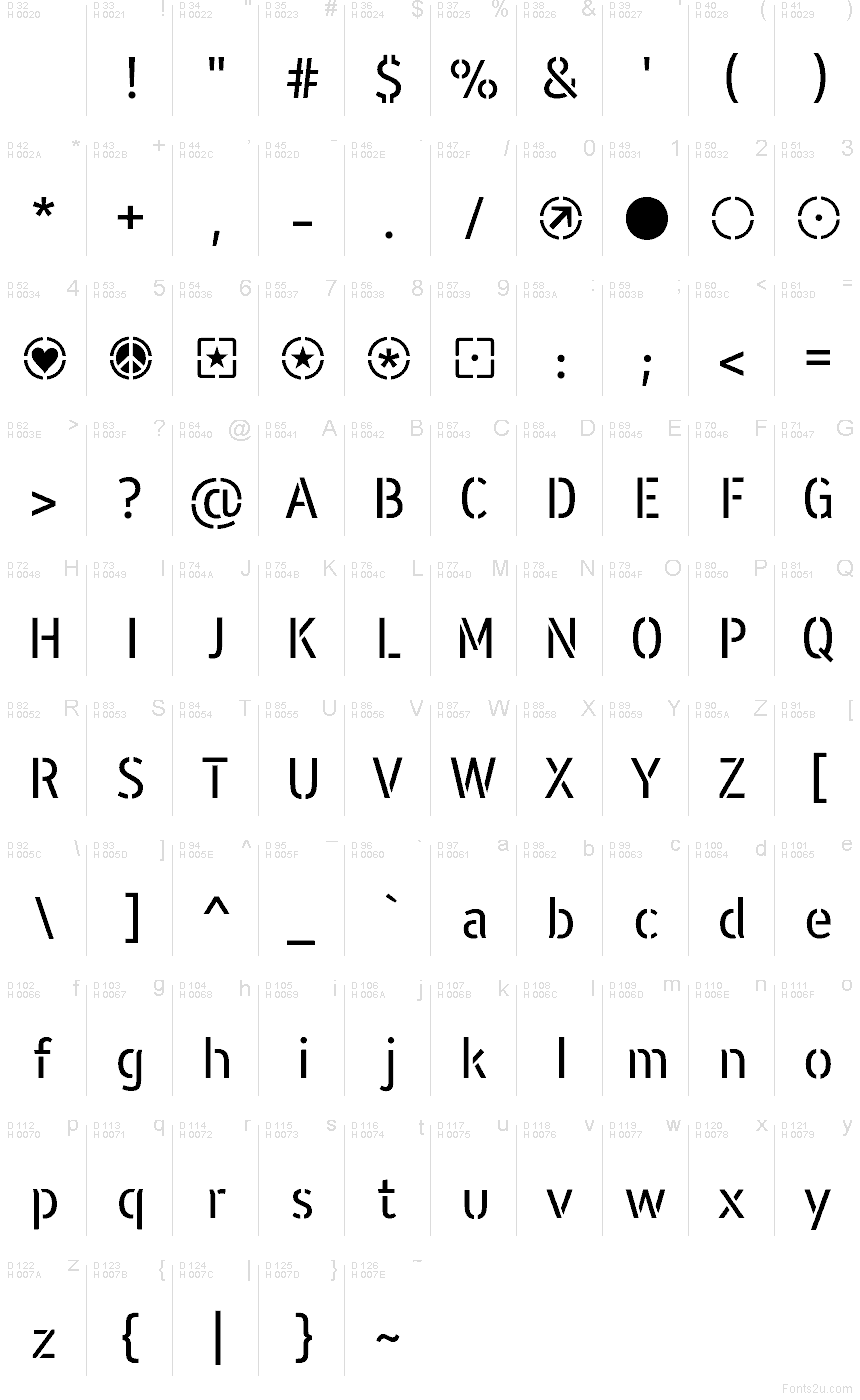
WARFIELD Regular
Warfieldは、Fernando Haro(deFharo)による無料のミリタリーステンシル書体です。シャープで統制の取れた表情が特徴で、縦長で細身のレターフォルム、切れ味のあるカット、均一な抜きが、金属製のコンテナや車両パネルにスプレーでマーキングしたような雰囲気を生み出します。無骨でタクティカルな存在感がありながら、視認性はしっかり確保。タイトな字間と硬質な垂直線が緊張感と切迫感を演出し、アクション、対立、戦略といった世界観を瞬時に伝えます。
書体Warfieldは、エアソフトやペイントボールのチームブランディング、ゲームタイトル、映画ポスター、タクティカルギアのパッケージ、イベントサイン、力強いスポーツグラフィックなど、武骨で兵営的なエネルギーを求めるデザインに最適です。この無料フォントは大きめのサイズで特に映え、ステンシル特有の抜きが明快に生きてきます。本文にはクリーンな幾何学系サンセリフを合わせると、レイアウト全体を力強く、読みやすくまとめられます。